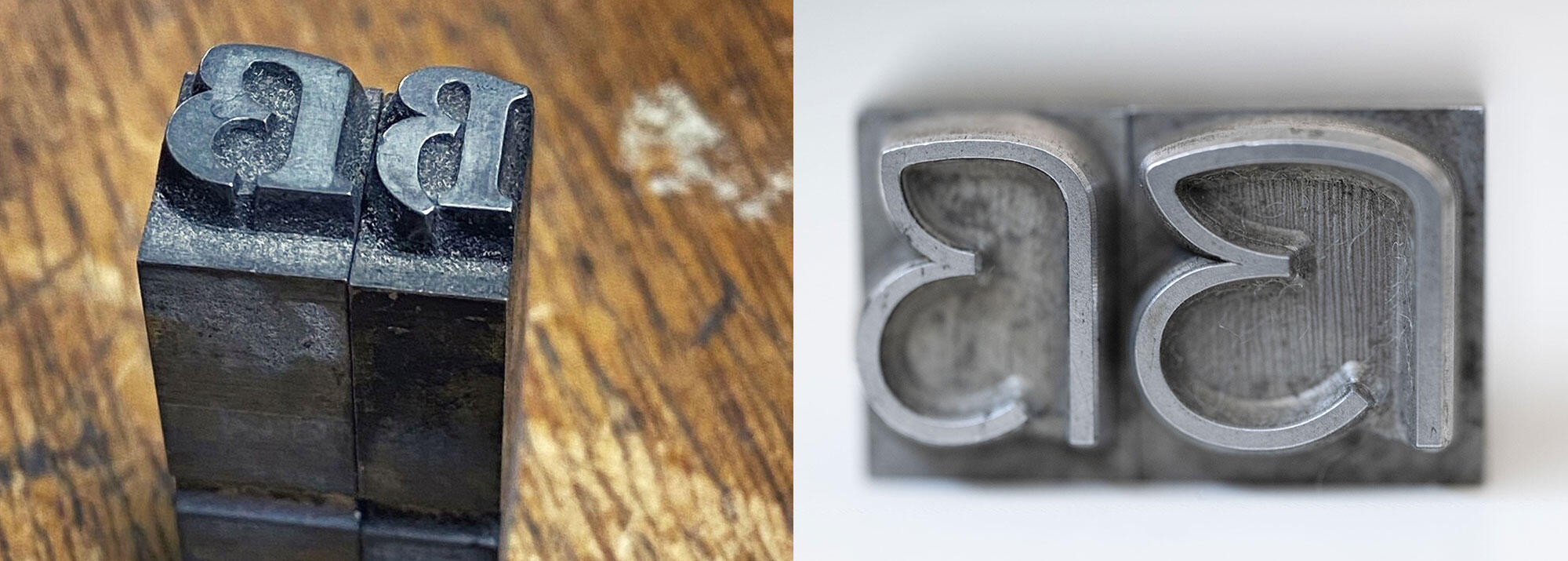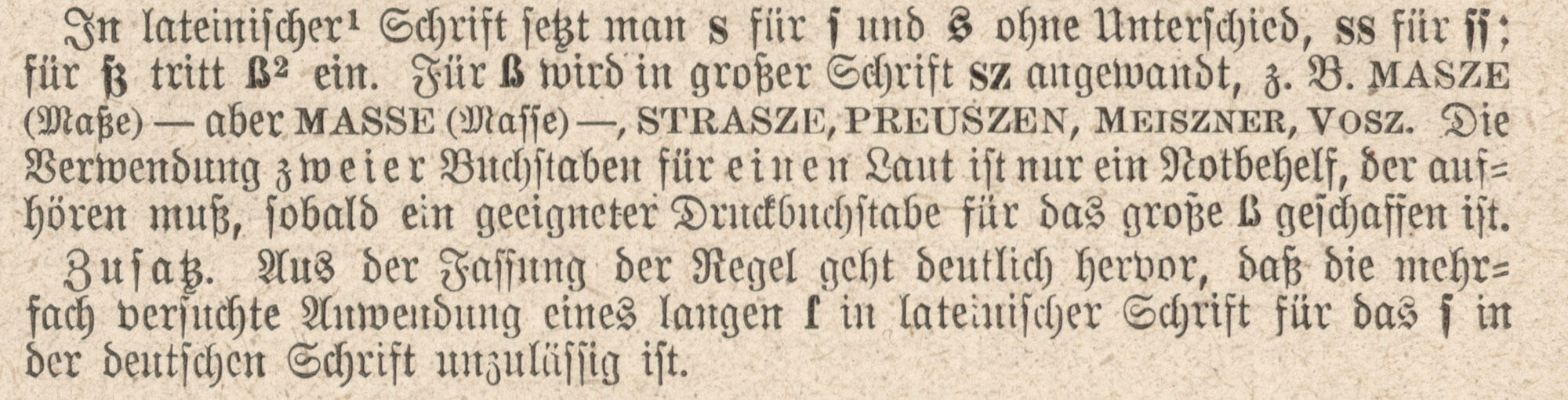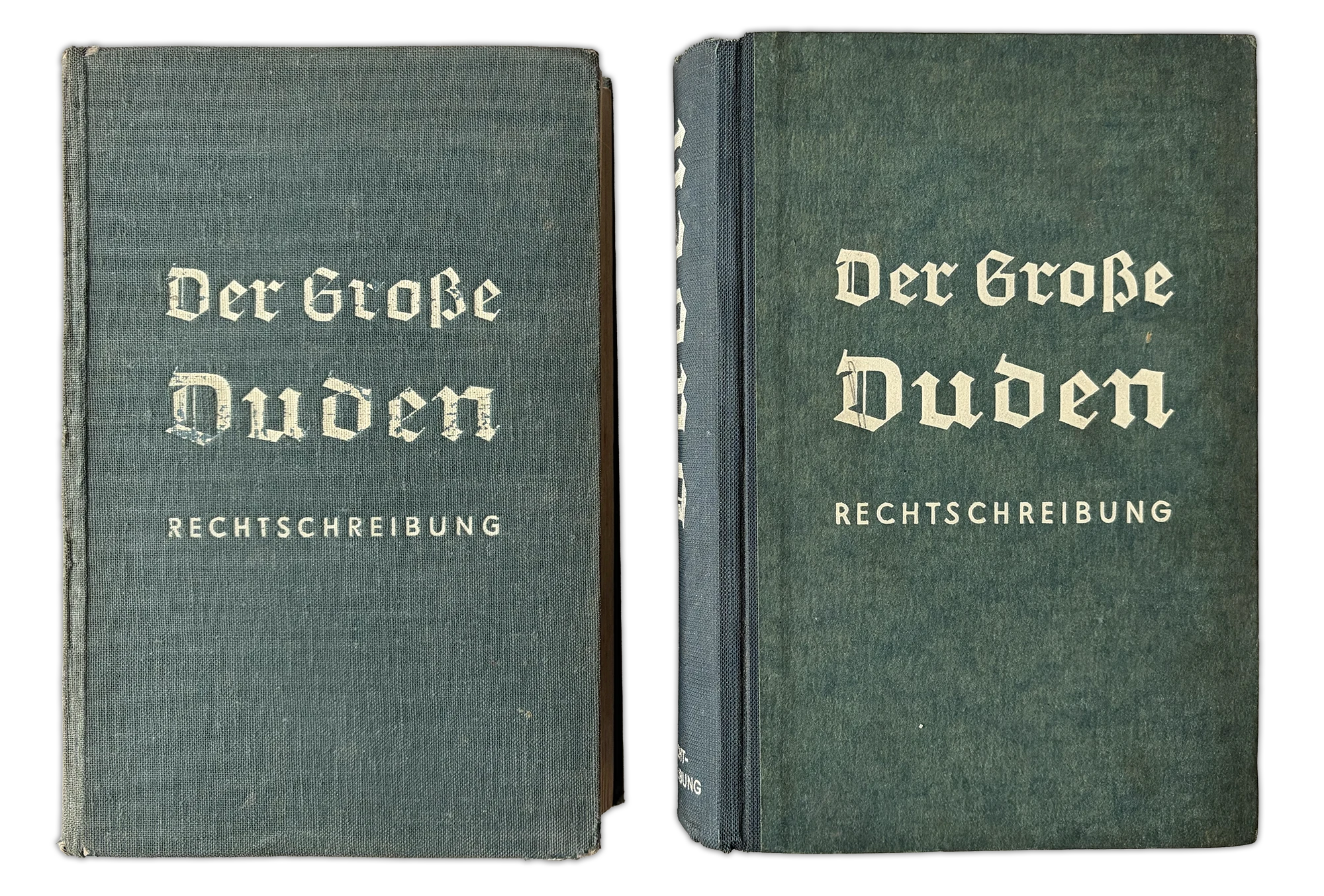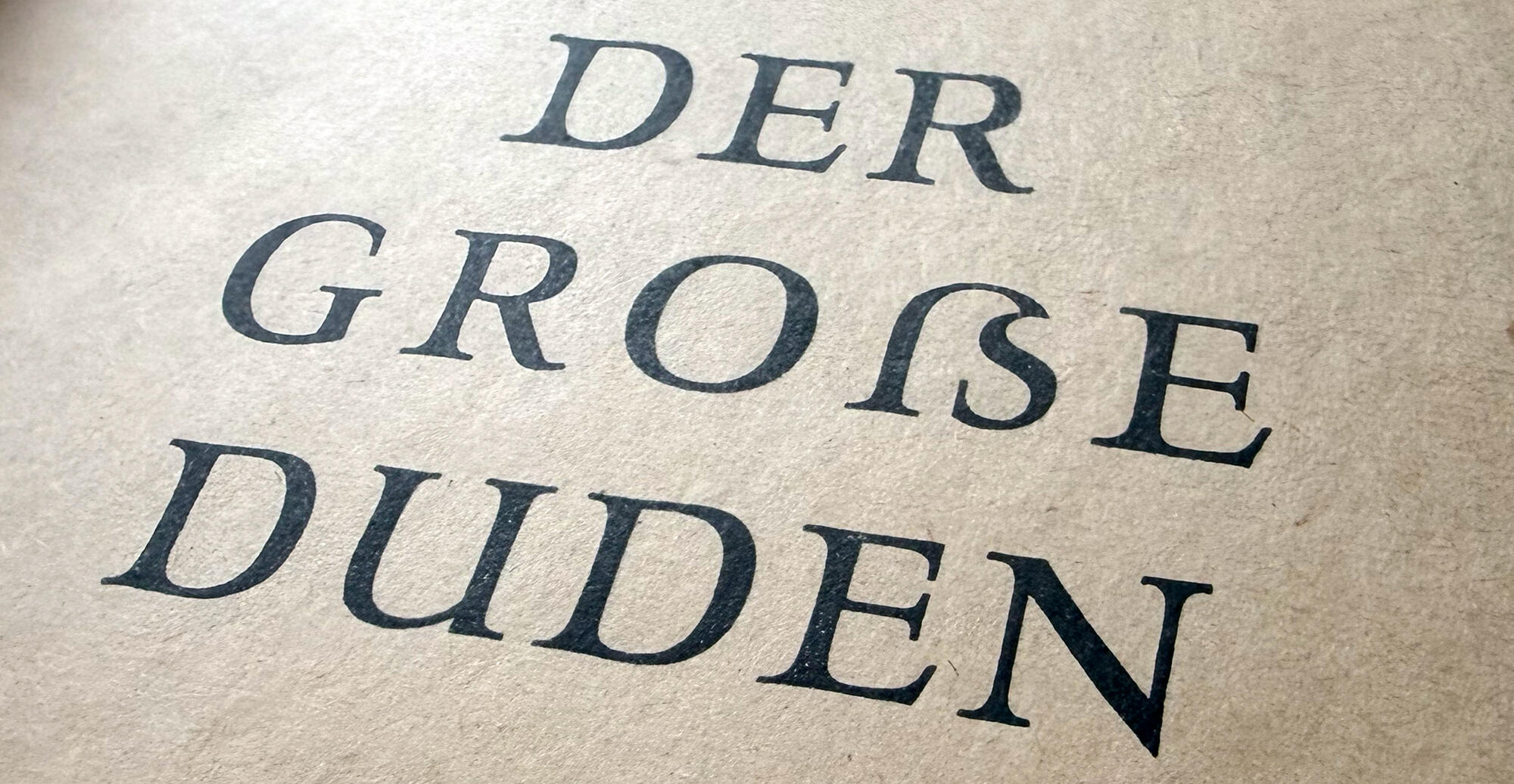
Die Arbeit von Konrad Duden hatte einen entscheidenden Einfluss auf die Etablierung einer einheitlichen deutschen Rechtschreibung. Duden engagierte sich aber auch im typografischen Kontext, etwa als Mitbegründer des Altschriftvereins oder als langjähriger Unterstützer des Eszett-Buchstabens in seiner kleinen und großen Form. Letzteres soll hier einmal genauer beleuchtet werden. Wir werfen einen Blick auf die Aussagen zur Schreibweise des ß im Versalsatz über sämtliche Duden-Ausgaben hinweg.
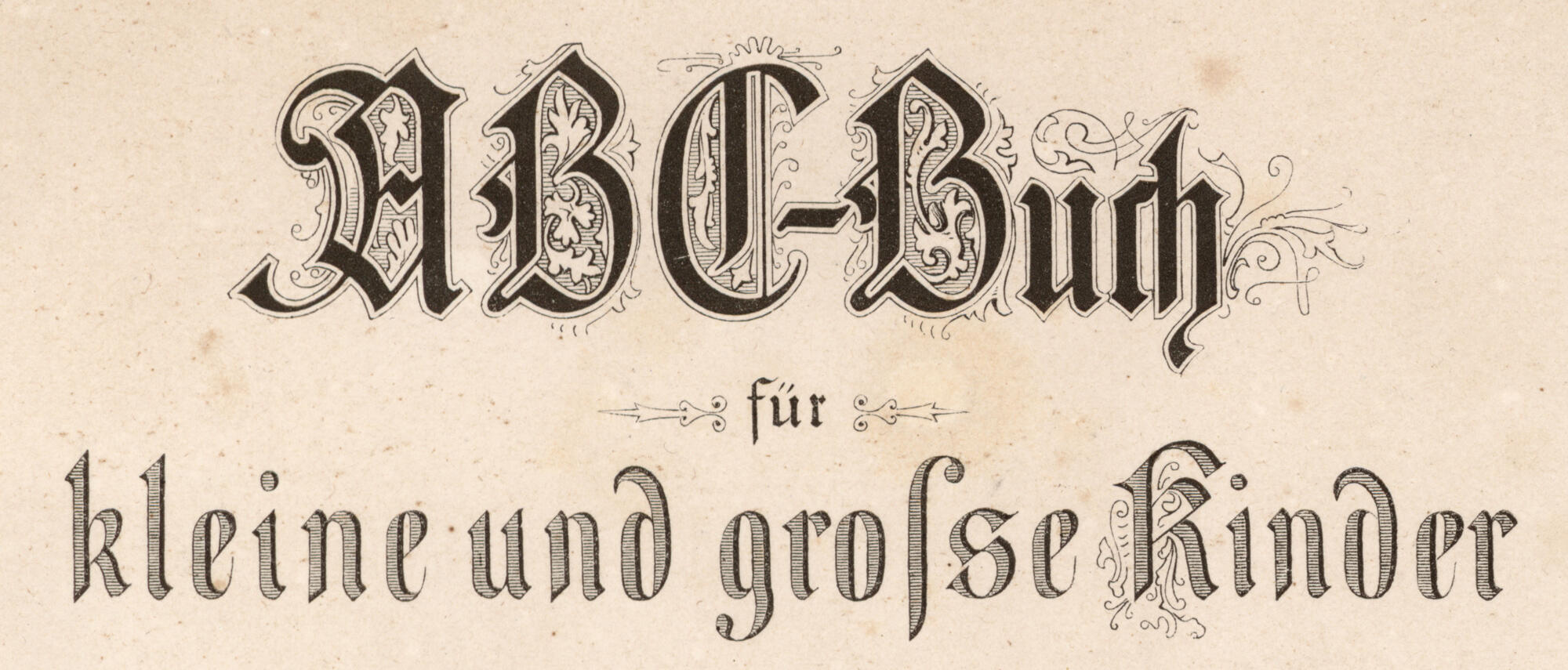
Im 19. Jahrhundert herrschte bei der Schreibung der s-Laute noch ein reichliches Chaos und dies schließt auch das Eszett ein. Dessen Einsatz war zwar in gebrochenen Schriften einigermaßen klar, in Antiqua aber war das Zeichen noch gar nicht etabliert und man konnte es sich allenfalls auf Anfrage von den Schriftgießereien anfertigen lassen. Anfangs halfen sich die Druckereien meist mit der Ersatzschreibweise »ſs«, die der Form des Fraktur-ß zumindest ähnelte. Im Laufe des 19. Jahrhunderts verzichtete man aber zunehmend auf das ſ und für das ß trat dann meist »ss« ein. Ausſchluß in Fraktur wurde zu »Ausschluss« in Antiqua. Der einflussreiche Jacob Grimm grätschte dann Mitte des 19. Jahrhunderts noch mit seiner bevorzugten Schreibung »sz« dazwischen (»Ausschlusz«). So waren zur Repräsentation eines Buchstabens also ganze vier Schreibweisen (ß, ſs, ss und sz) parallel im Einsatz und dabei wurden noch nicht einmal alle, sondern nur die am meisten verwendeten Varianten berücksichtigt.
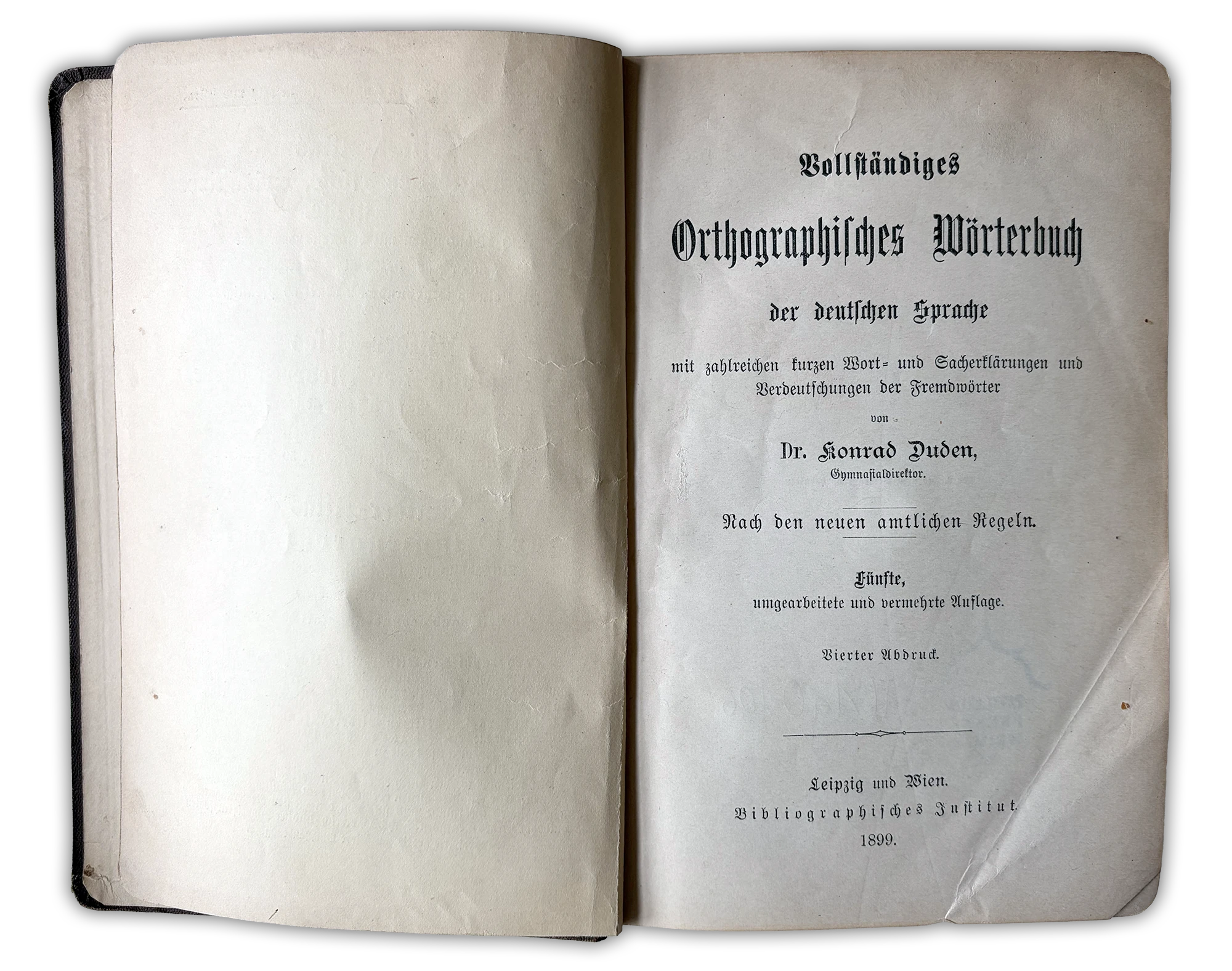
1880 erschien der sogenannte Ur-Duden als »Vollständiges Orthographisches Wörterbuch der deutschen Sprache« im Verlag Bibliographisches Institut Leipzig. Konrad Duden legte damit den Grundstein für eine deutsche Einheitsorthografie. Nach dem politischen Scheitern der 1. Orthographischen Konferenz (1876) setzte sich Dudens Werk nach und nach im gesamten Reich durch, zunächst auch ohne amtliche Unterstützung und sogar gegen ausdrücklichen Widerstand, etwa durch Reichskanzler Bismarck. Dabei half auch, dass das Werk im Wesentlichen mit der preußischen und bayrischen Schulorthografie im Einklang stand. Auch Setzer, Drucker und Korrektoren richteten sich in der Folge immer mehr in orthografischen Fragen nach diesem Wörterbuch.
Zum Antiqua-Eszett heißt es im Ur-Duden:
Die S-Laute in lateiniſcher Schrift.
Zu merken iſt, daß man in lateiniſcher Schrift s für ſ und s ohne Unterſchied, ss für ſſ und ſs für ß anwendet. Statt ſs iſt auch ß zuläſſig.
Diese Regel ist in durchaus bemerkenswert. Für die zwei s-Formen wurden die Modernisierungsbestrebungen der Zeit aufgenommen und nur noch die Schreibung mit rundem s zugelassen. Der dadurch zementierte Bruch in den Satzregeln zwischen Antiqua- und Frakturschreibung wurde also bewusst in Kauf genommen. In gleichem Sinne hätte auch das Eszett leicht abgeschafft und durch zum Beispiel »ss« oder »sz« ersetzt werden können. Stattdessen wurde es aber ausdrücklich in die Antiqua übernommen. Und dies obwohl die gleiche Regel den ersten Bestandteil der Schreibung »ſs« in seiner einzelnen Anwendung für die Antiqua ausdrücklich verbot. Das Eszett war für die Wiedergabe der deutschen Sprache zu wichtig geworden und nicht mehr nur ein Zeichen des Fraktursatzes.
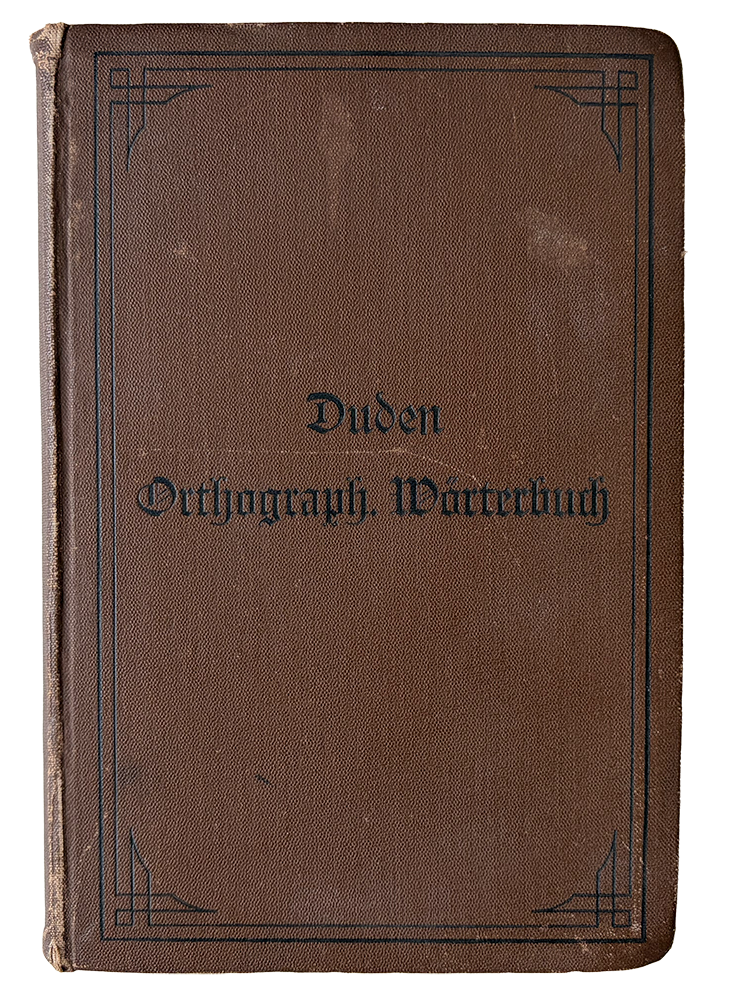
Dass hier zunächst »ſs« die Hauptform war, zeigt ein typisches Henne-Ei-Problem bei der Fortentwicklung des Alphabets seit dem Buchdruck mit beweglichen Lettern. Vertreter der Rechtschreibung können nicht einfach Buchstaben erfinden. Sie könnten ja nicht einmal die entsprechenden Regeln in gedruckter Form verbreiten. Sie müssen auf dem aufbauen, was von Schriftgießereien angeboten und in Druckereien vorhanden ist. Doch warum sollte man sich in Gießereien und Druckereien die Mühe machen, neue Zeichen zu entwickeln respektive vorzuhalten, wenn es keine Rechtschreibregeln gibt, die sie legitimieren. Schrittweise Einführungen mit Varianten – wie wir sie hier sehen – sind also kein Zufall.
In der Auflage von 1888 erhielt die Antiqua-Eszett-Regel dann eine neue, interessante Fußnote:
Preußen verlangt ſs, Württemberg ß. Da die Anwendung zweier Buchſtaben für einen Laut ein Notbehelf iſt und namentlich für die Schüler, z. B. bei der Silbentrennung, etwas Irreführendes hat, ſo verdient ß den Vorzug. Nur muß es in einer Weiſe dargeſtellt werden, daß es nicht aus dem Charakter der lateiniſchen Schrift herausfällt.
Konrad Duden bekannte sich hier klar zum Eszett als einzelner Buchstabe und begründete dies auch. Er sah im Eszett die Repräsentation eines Lauts und dies verlangte für ihn einen einzelnen Buchstaben – alles andere wäre nur ein »Notbehelf«.
Die 2. Orthographische Konferenz im Jahr 1901, an der auch Konrad Duden teilnahm, war dann die endgültige Verwirklichung der einheitlichen deutschen Rechtschreibung. Die Regeln traten nun amtlich für Deutschland, Österreich und die Schweiz gleichermaßen in Kraft. Zu den S-Lauten in Antiqua heißt es nun:
Amtliche Rechtschreibung von 1901
In lateiniſcher Schrift ſteht s für ſ und s, ss für ſſ, ß (beſſer als ſs) für ß, für ß tritt in großer Schrift sz ein, z. B. MASZE (Maße), aber MASSE (Maſſe).
Das kleine Eszett wurde damit ausdrücklich für die Antiqua bestätigt und die Schriftgießereien im deutschsprachigen Raum verständigten sich in der Folge auf die Einführung des kleinen Eszett in sämtliche Schriftarten ab 1903/04. Die zeitgleiche Einführung eines großen Eszett wurde 1903 besprochen, letztlich aber vertagt.
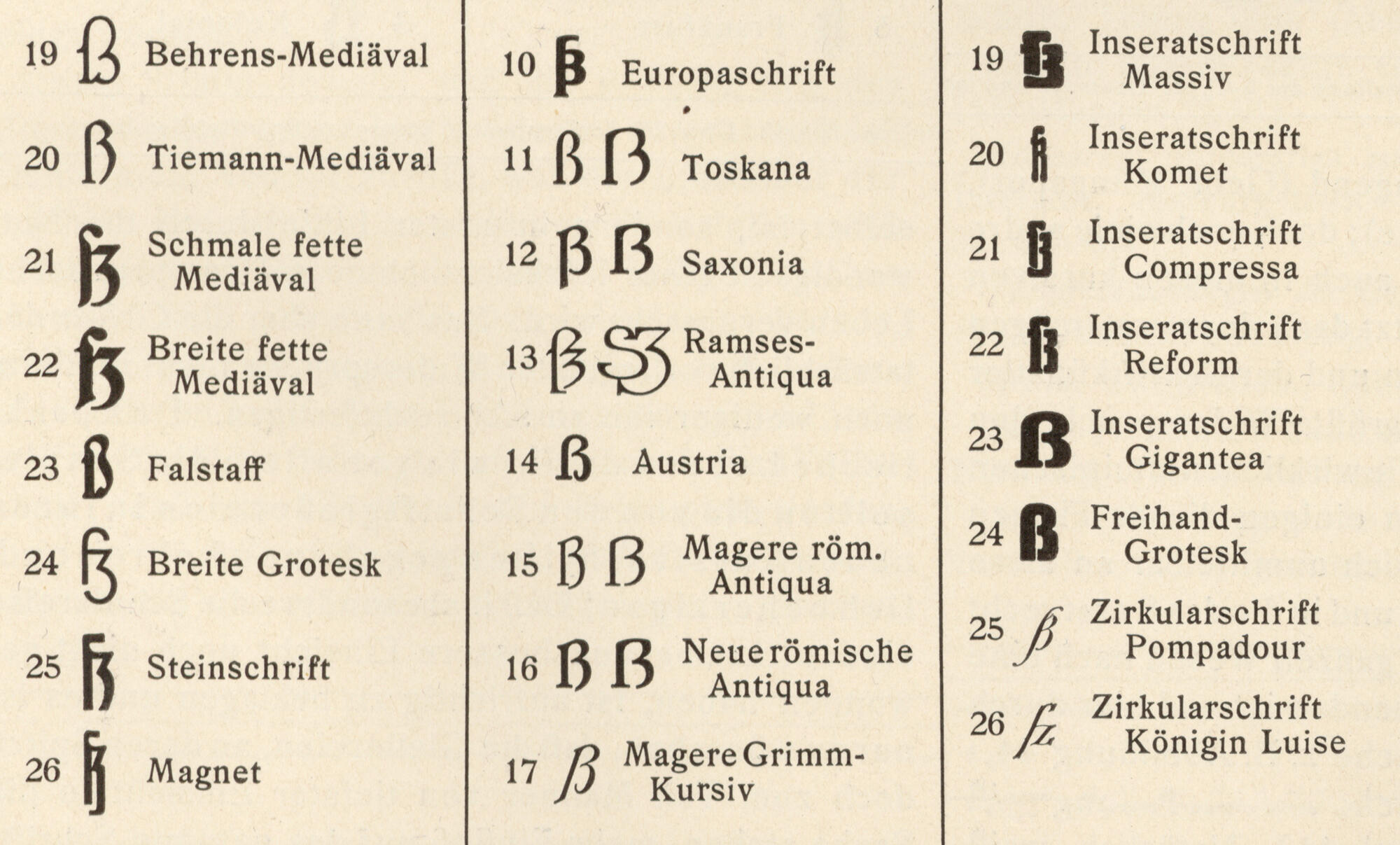
Beispiele neuer Antiqua-Eszett-Formen im frühen 20. Jahrhundert
Das Eszett im Versalsatz
Mit den amtlichen Vorgaben bekam nun auch die Versal-Schreibweise des ß in Antiqua erstmals eine klare Regel, die überraschenderweise aber von der üblichen Ersatzschreibung mit Doppel-S abwich. Wie schon erwähnt, konnten die Rechtschreibvertreter nicht einfach einen Buchstaben erfinden. Ein großes Eszett war zwar schon seit 1879 diskutiert worden, fand sich aber noch nicht in gängigen Satzschriften. Grund für die gewählte neue SZ-Regel war die bessere Repräsentation des Eszett im Versalsatz, die durch das Beispiel MASZE/MASSE demonstriert wurde. In Fachkreisen kam diese Regel jedoch nicht sonderlich gut an und wurde vielfach auch einfach ignoriert. Zu sehr hatte man sich schon an Schreibweisen wie PREUSSEN gewöhnt. Und diese Gewöhnung hatte ein Gefühl einer Richtigkeit erzeugt. Die Schreibweise PREUSZEN wurde in Fachkreisen als hässlich und fremdländisch wirkend beschrieben.
Nichtsdestotrotz war die bloße Existenz einer einheitlichen amtlichen Rechtschreibung im Grundsatz ein Segen für das druckgrafische Gewerbe. Nur an einer Sache störte man sich noch sehr: es gab noch zu viele Varianten. Man wollte mehr Eindeutigkeit. So kam es zu Gesprächen mit Konrad Duden über die Erstellung eines speziellen Dudens für das druckgrafische Gewerbe. Dies scheiterte jedoch an den vertraglichen Beziehungen Dudens mit dem Bibliographischen Institut und so wurde das Buch letztlich vom Verlag selbst angeboten. Im neuen Buchdrucker-Duden taucht die obige Regel dann folgendermaßen auf:
STRASSE, AUSSEN, FUSSBALL
Auch: STRAẞE, AUẞEN, FUẞBALL
Die Formulierung ist dabei zurückhaltender als in der amtliche Rechtschreibung selbst. Dort ist seit 2024 das große Eszett die Hauptform und die Schreibung mit SS ist die mögliche Variante geworden.
Doch wie dem auch sei: Konrad Dudens Wunsch aus dem Jahr 1888 ist erfüllt. Die vielen Varianten des 19. Jahrhunderts und die Notlösungen des 20. Jahrhunderts sind nicht mehr nötig. Das Eszett kann als ein Buchstaben für einen Laut in groß und klein dargestellt werden:
Der große Duden
DER GROẞE DUDEN